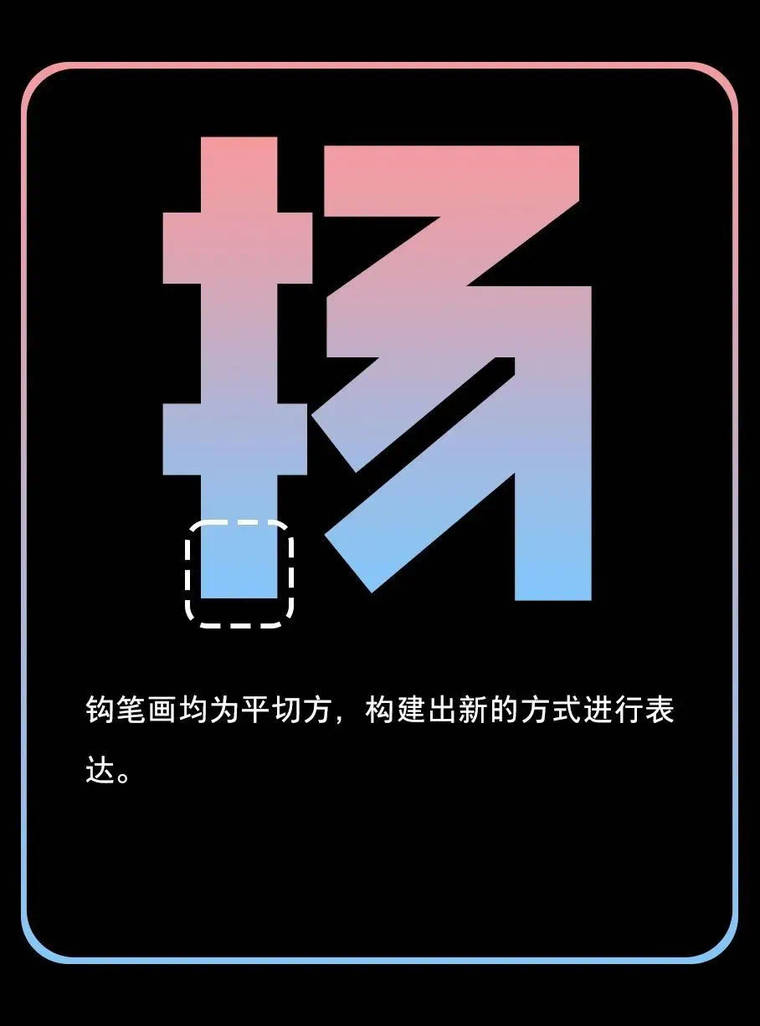
联想小新潮酷体
联想小新潮酷体,这款字体结构工整、笔画清晰,兼顾美观与易读性,适用于标题、正文、海报、包装、LOGO 等多种场景。字形优雅稳定,风格百搭耐看,适配日常排版与创意设计,让文字呈现更舒适、更具质感。联想小新潮酷体一笔一画,皆是细节,以均衡的比例、流畅的线条打造舒适视觉体验,字形端正大气,风格简约现代。无论是商业设计、品牌宣传还是日常排版,都能轻松驾驭,让文字更有格调与力量。联想小新潮酷体字体下载。
联想小新潮酷体字体介绍
一款潮酷的黑体字,略窄的字面、纯直的结构、精简的笔画,使字体呈现年轻态和潮流感。字面相对于常规字体缩窄,整体略瘦长,区别于传统黑体的方正感,更加年轻前卫、时尚新潮。